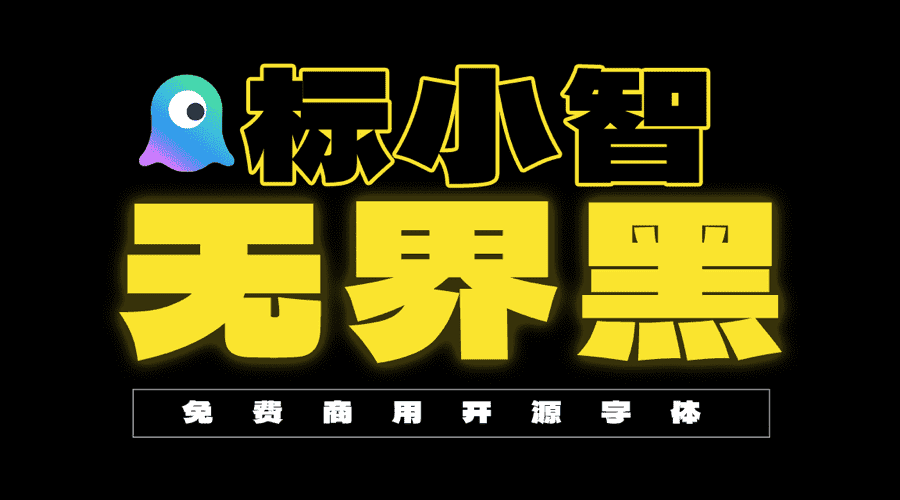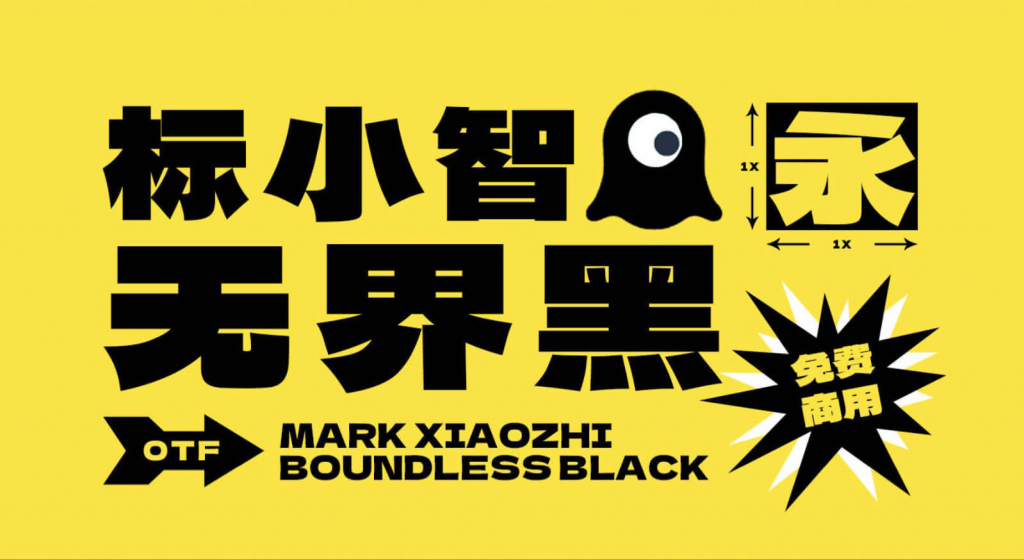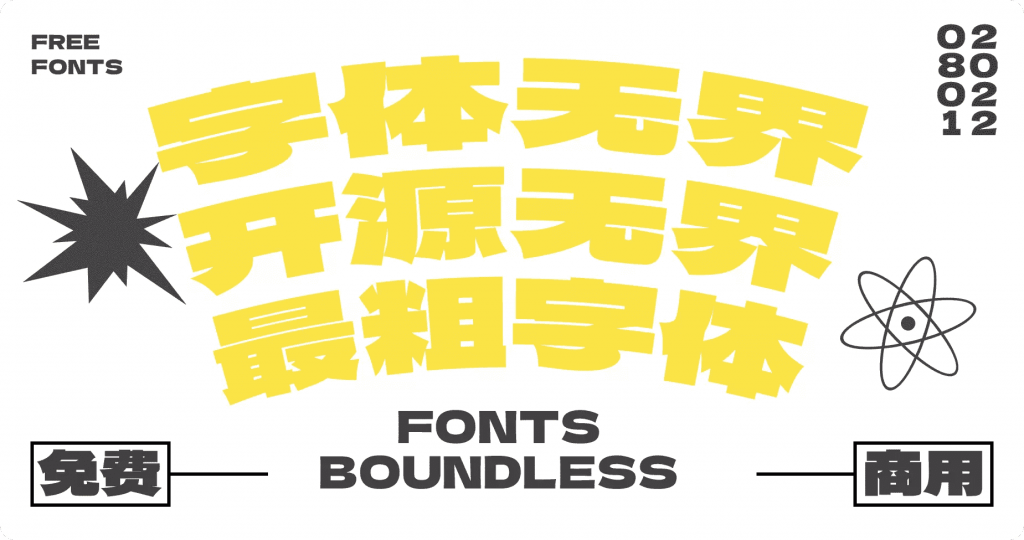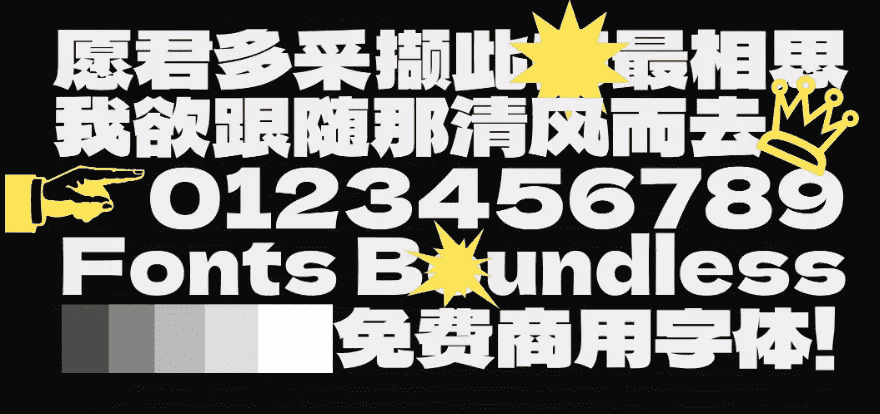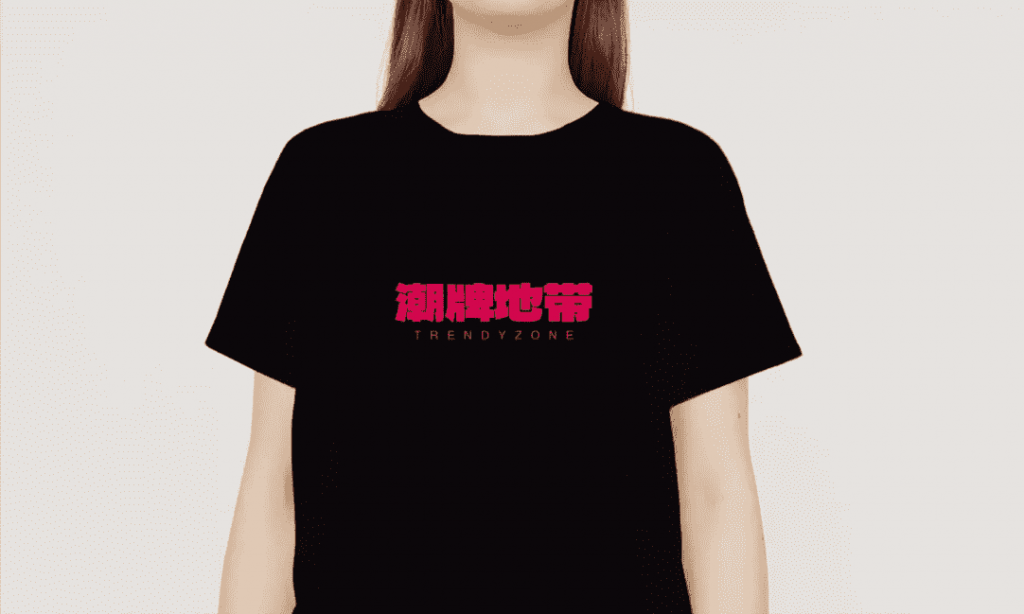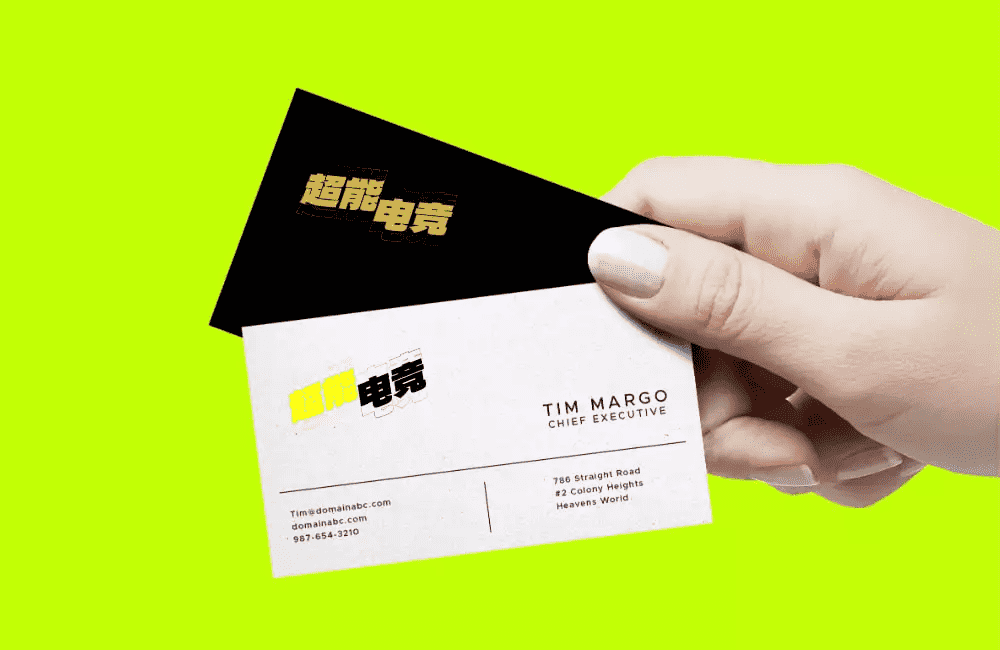
我们介绍的免费商用字体——德拉黑体(Dela Gothic),在猫啃网的牵头下,简体中文版经过将近6个月的打磨,终于如期而至!补字工作按GB2312标准完成,简体中文再也不会缺字了!
标小智无界黑,是由标小智LOGO神器携手猫啃网一起创作设计的第一款品牌字体,允许任何个人和企业免费使用,包括商用用途,无界无限制字如其名,愿为中文免费字体生态添砖加瓦,来一起看看这款非常酷的免费商用中文字体吧!
标小智无界黑是一款脱胎于日本开源字体——德拉黑体的超粗黑体,标小智无界黑按照GB2312-80字体标准来制作,从字库角度出发,将原字体中的汉字字形更改为更加符合国标的字形,在字体细节方面做到尽善尽美。
标小智无界黑字体应用案例
标小智无界黑字体结构扁平,笔画非常粗厚,同时带有明显的尖字体表现出非常高的稳定性和强有力的视觉表现,非常适合用于logo设计、标题、海报和包装等场合。